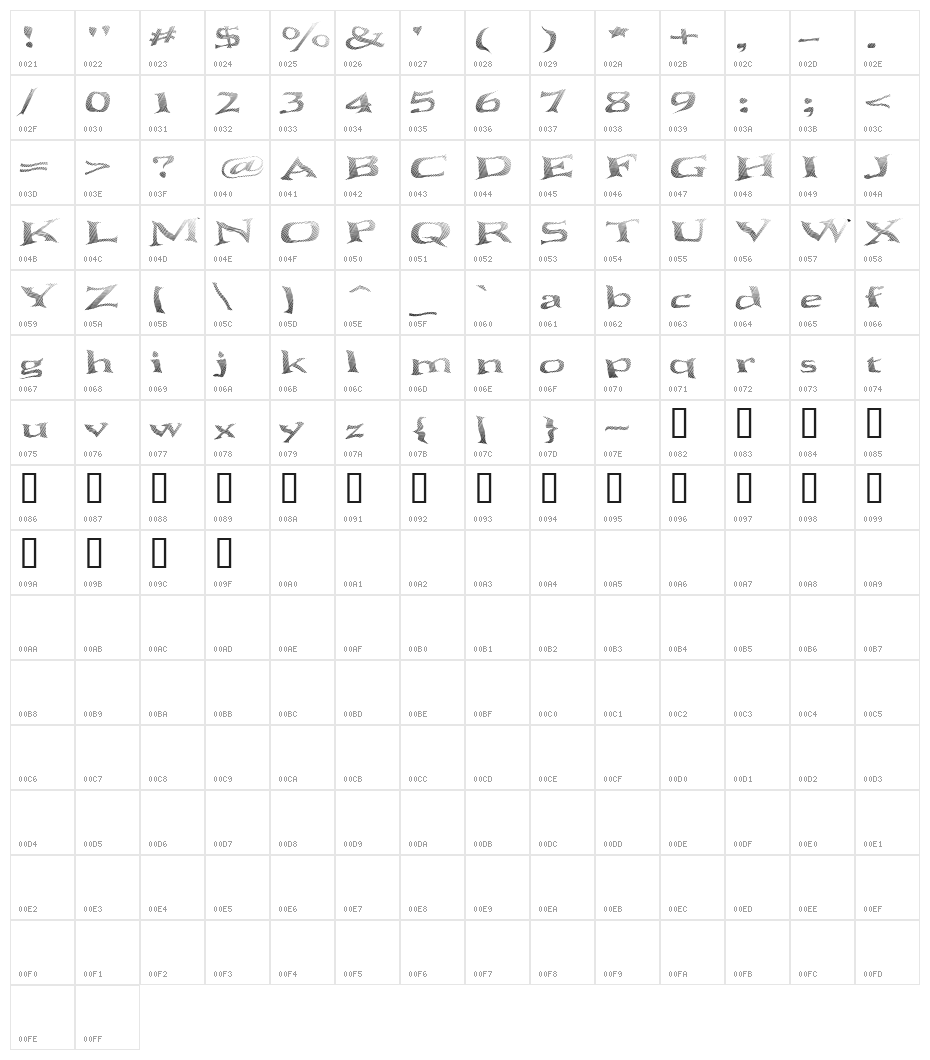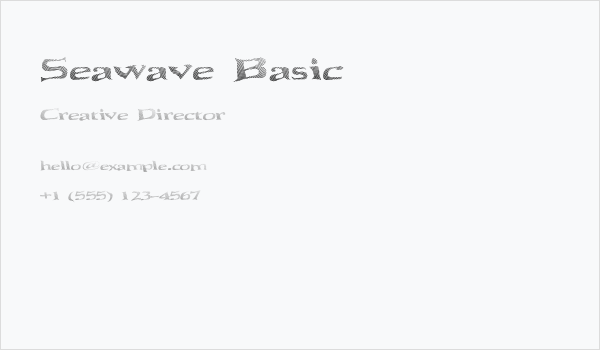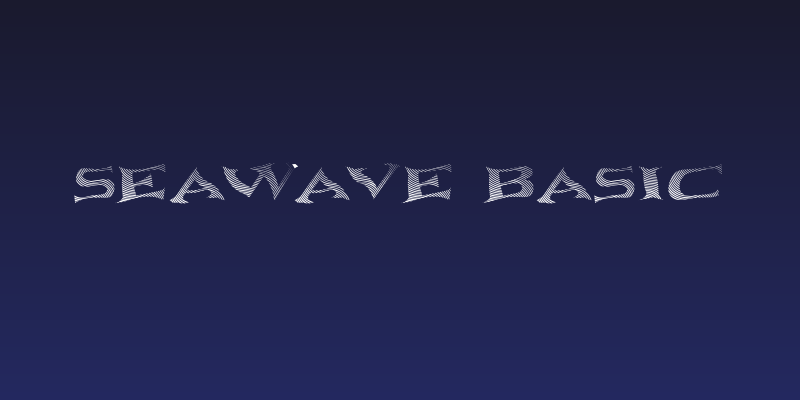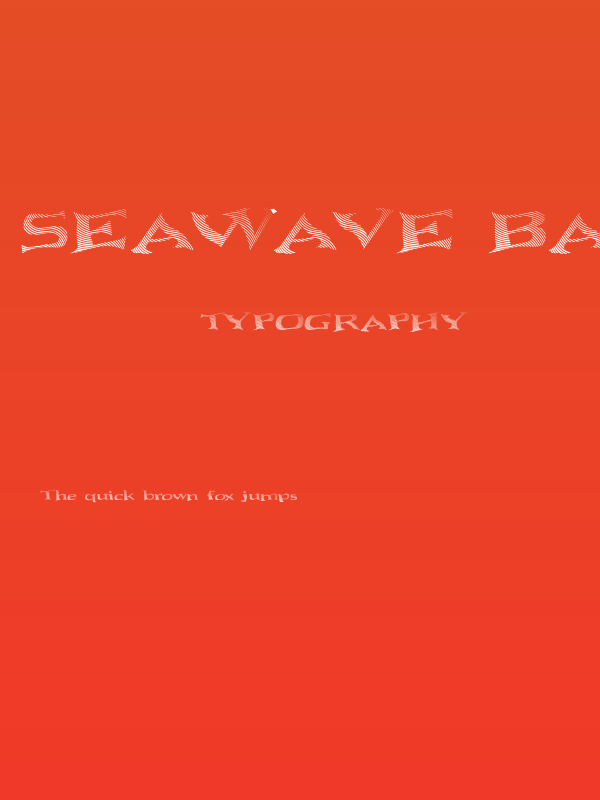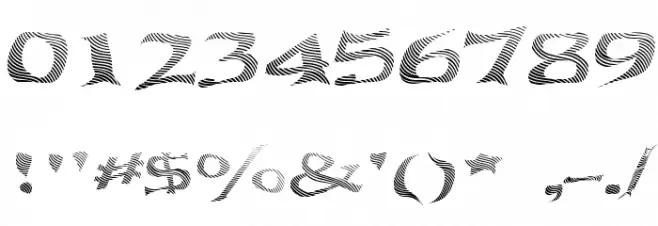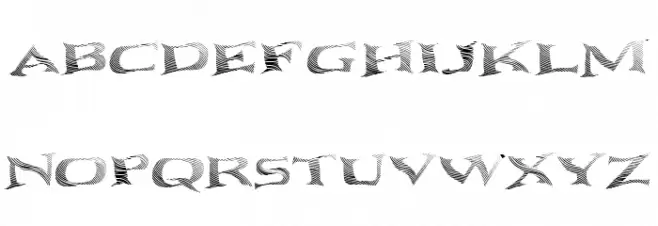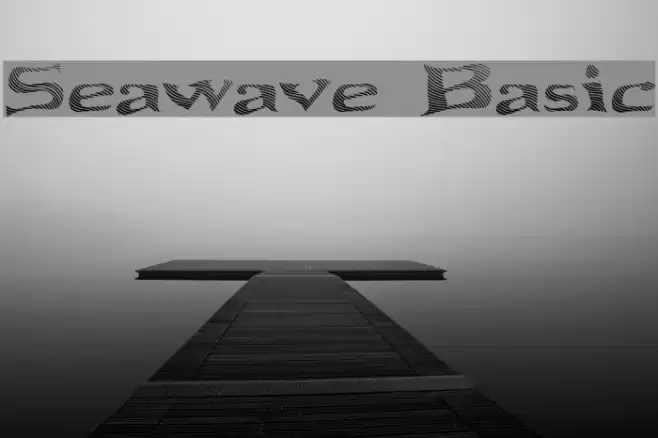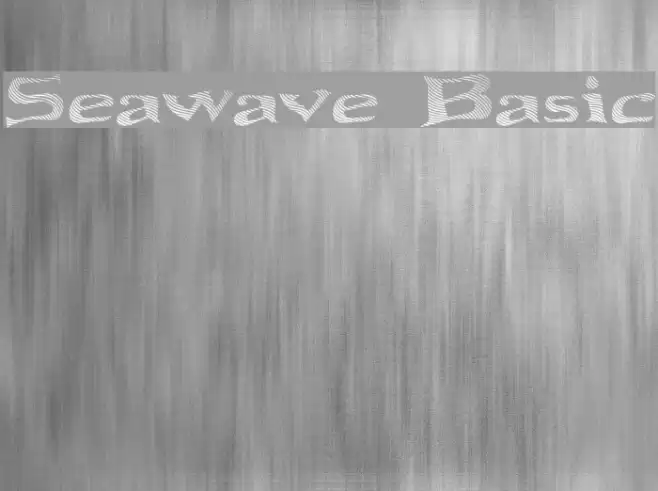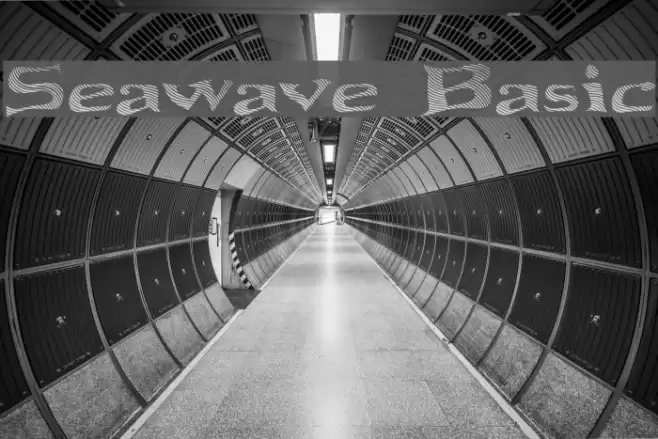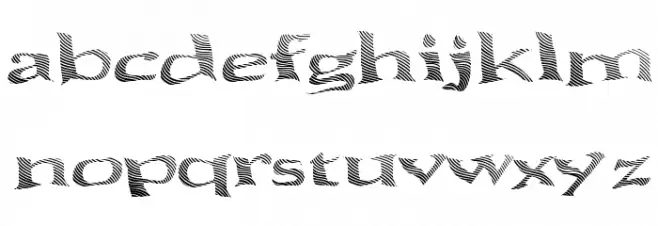
Seawave Basic Font
| Projets proposés | Ideal for creative projects such as posters, album covers, branding, and event invitations where a bold and artistic statement is desired. |